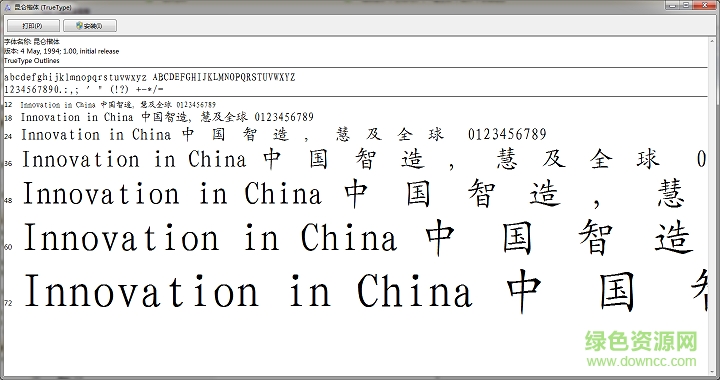
昆侖楷體是一款非常美觀的楷書字體,這款字體筆畫細(xì)膩,字體方正,不少朋友都比較喜歡,適合用于多個不同領(lǐng)域使用,有需要的用戶趕快下載體驗吧!
楷書也叫正楷、真書、正書。從程邈創(chuàng)立的隸書逐漸演變而來,更趨簡化,橫平豎直?!掇o?!方忉屨f它“形體方正,筆畫平直,可作楷模。”故名楷書。始于漢末,通行至現(xiàn)代,長盛不衰。
楷書的產(chǎn)生,緊扣漢隸的規(guī)矩法度,而追求形體美的進(jìn)一步發(fā)展,漢末、三國時期,漢字的書寫逐漸變波、磔而為撇、捺、且有了“側(cè)”(點)、“掠”(長撇)、“啄”(短撇)、“提”(直 鉤)等筆畫,使結(jié)構(gòu)上更趨嚴(yán)整。如《武威醫(yī)簡》、《居延漢簡》等。楷書的特點在于規(guī)矩整齊,是字體中的楷模,所以稱為楷書,一直沿用至現(xiàn)代。